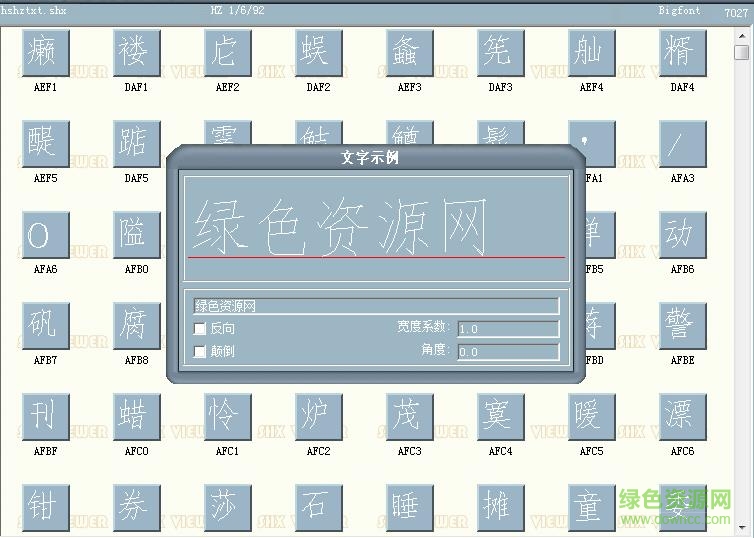
hshztxt.shx字體在用戶們所需要的cad字體中占據(jù)極廣泛的使用范圍,讓你無(wú)論是在cad制圖中或者是打開cad圖紙進(jìn)行看圖的過(guò)程中都需要此字體的支持,快來(lái)綠色資源網(wǎng)下載吧!
hshztxt.shx的多種用戶使得它能夠廣泛為人所用,讓你感受到不錯(cuò)的使用體驗(yàn),其內(nèi)的字體字里行間透露著青秀的氣息,在觀看的時(shí)候能夠感受到不錯(cuò)的視覺享受!